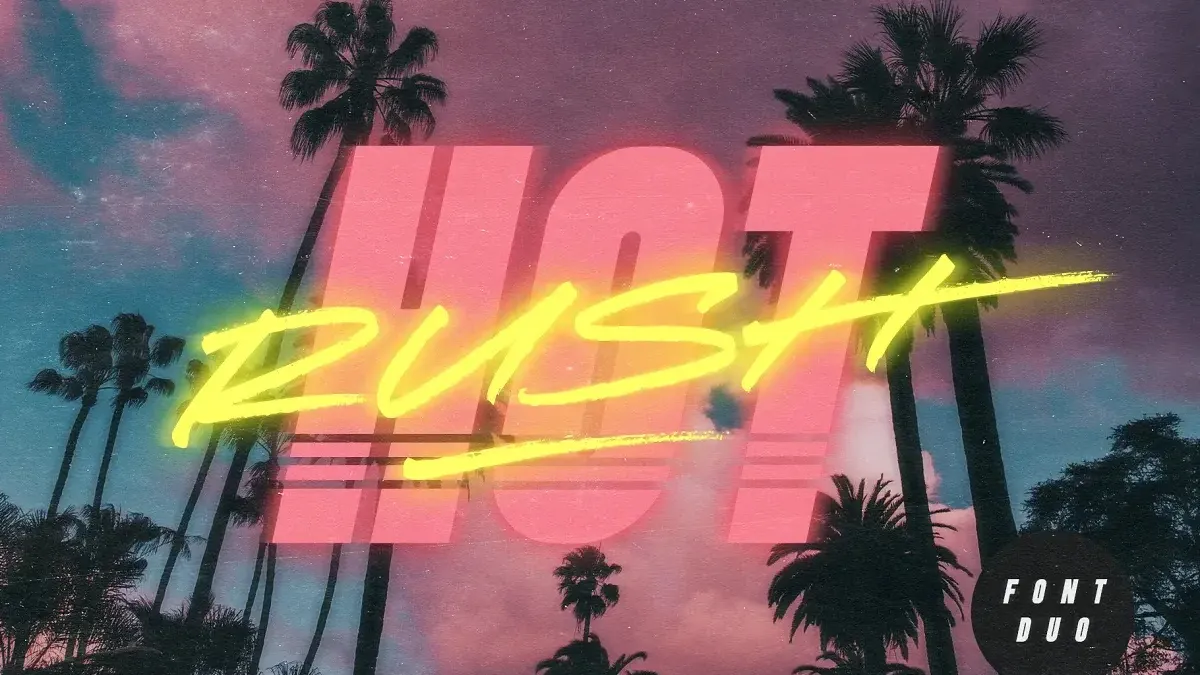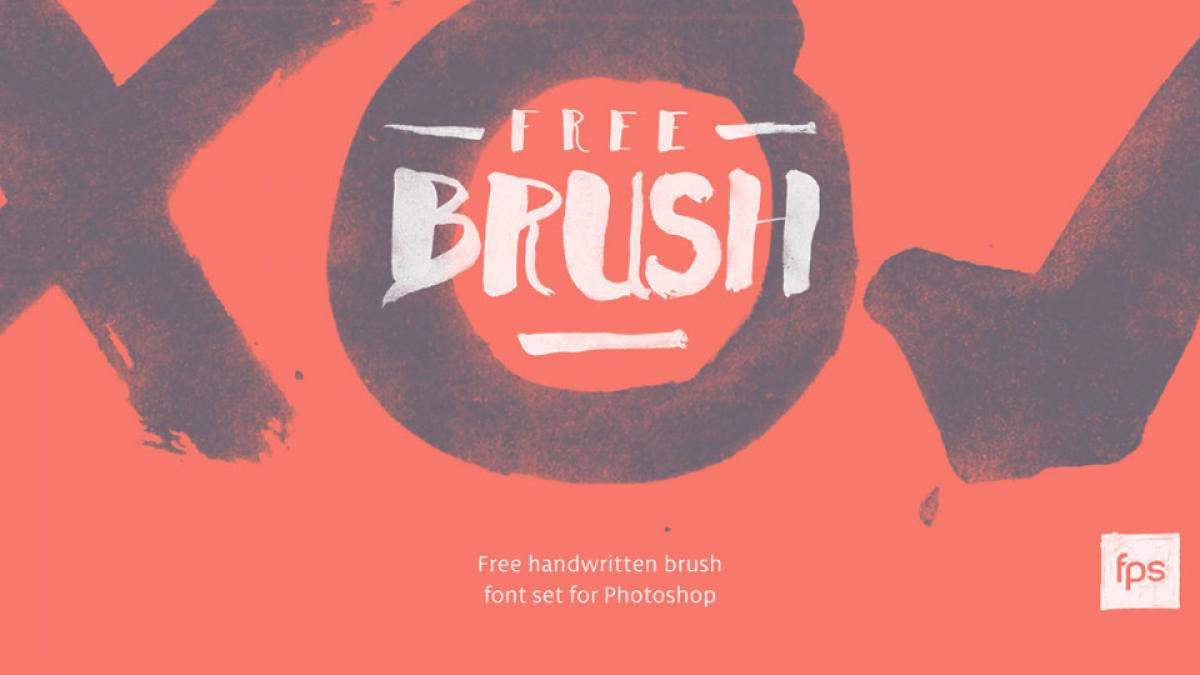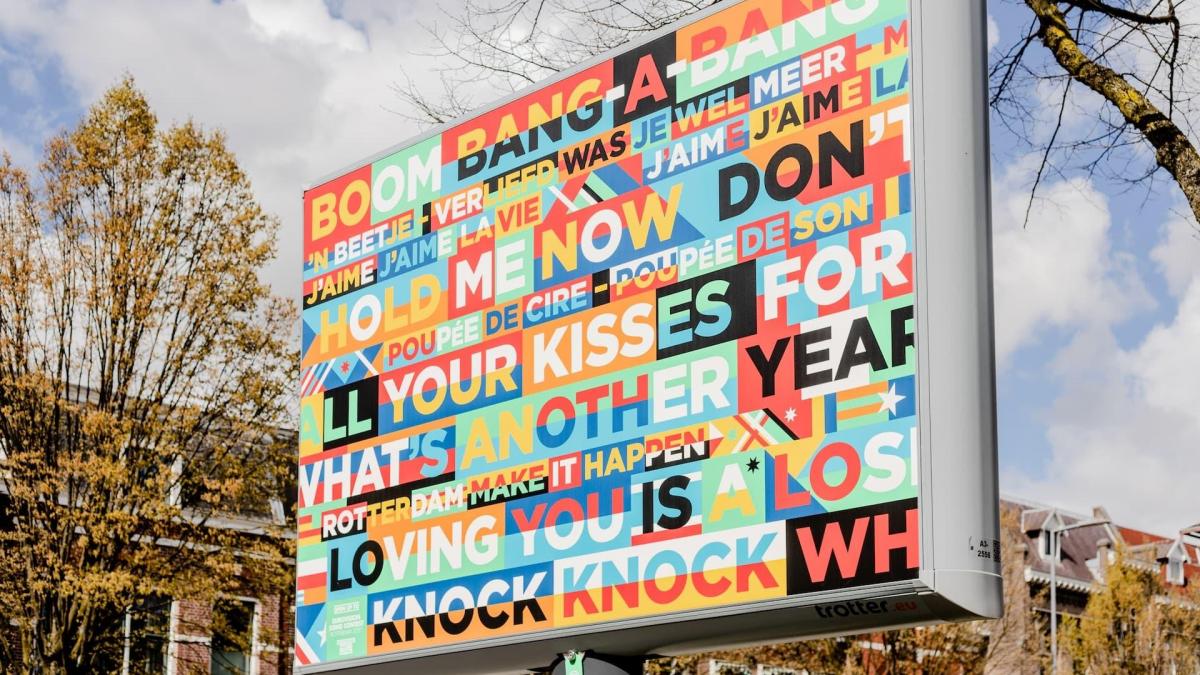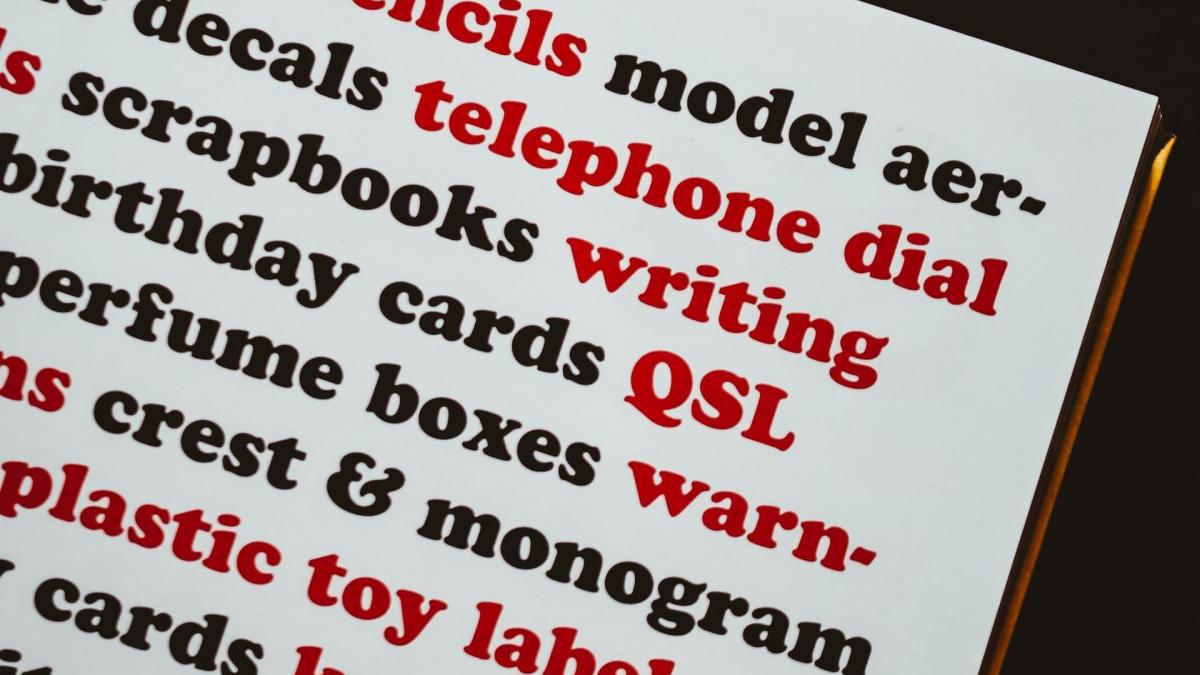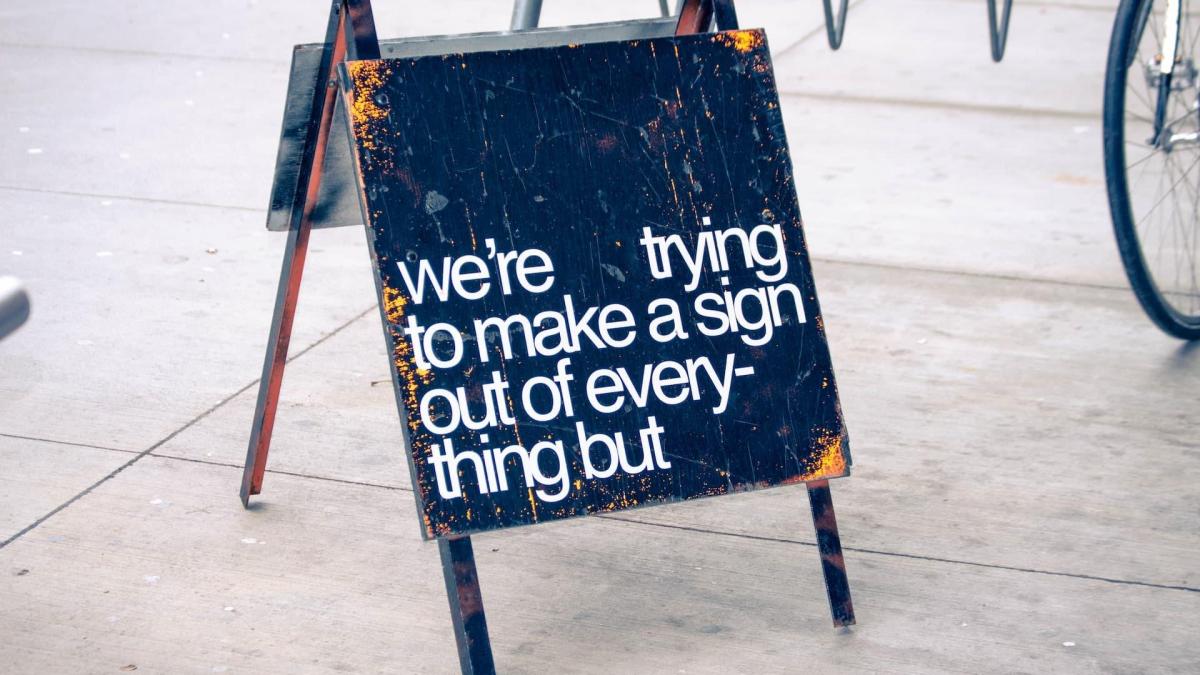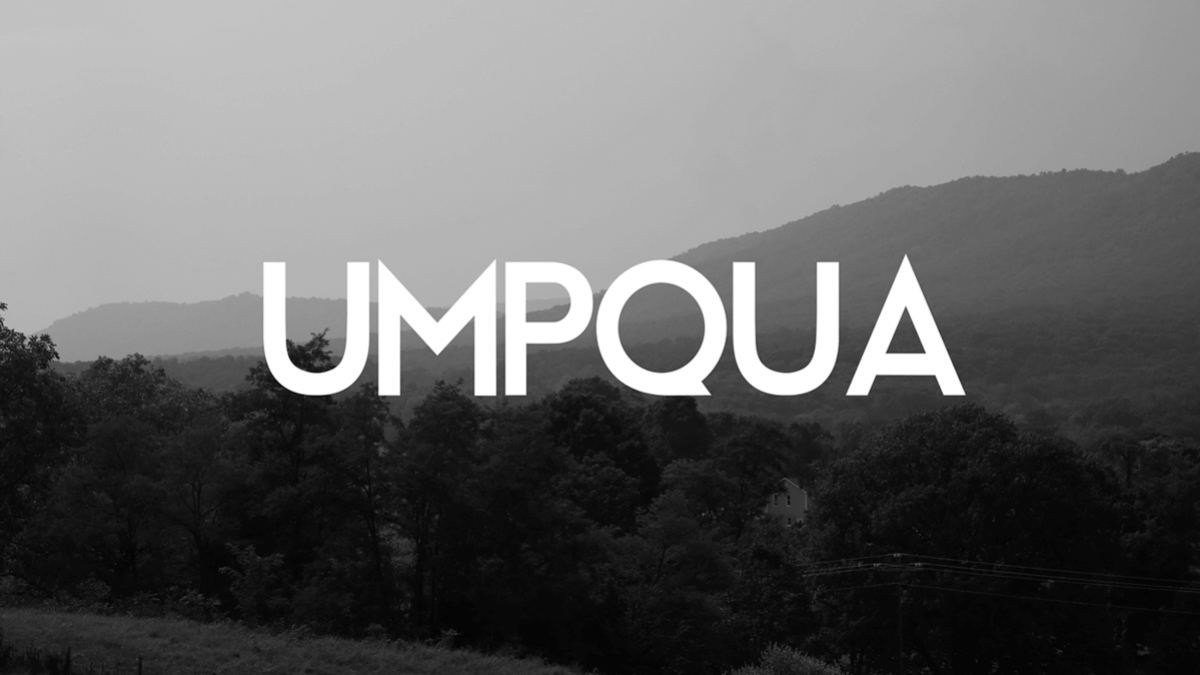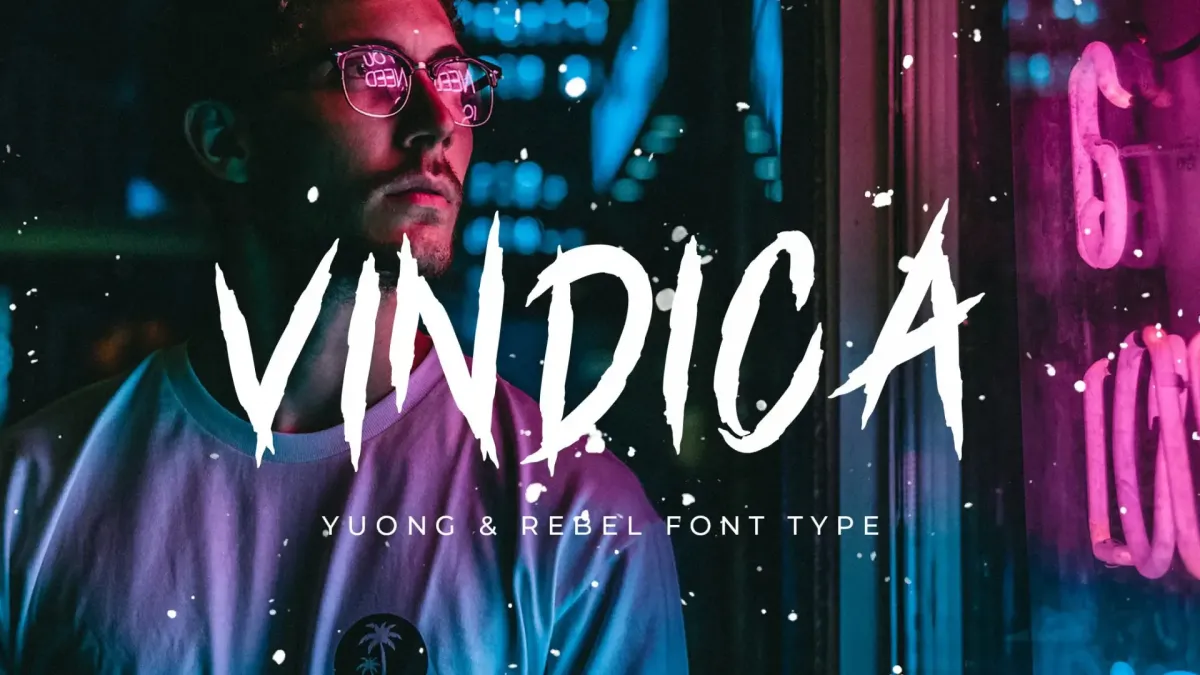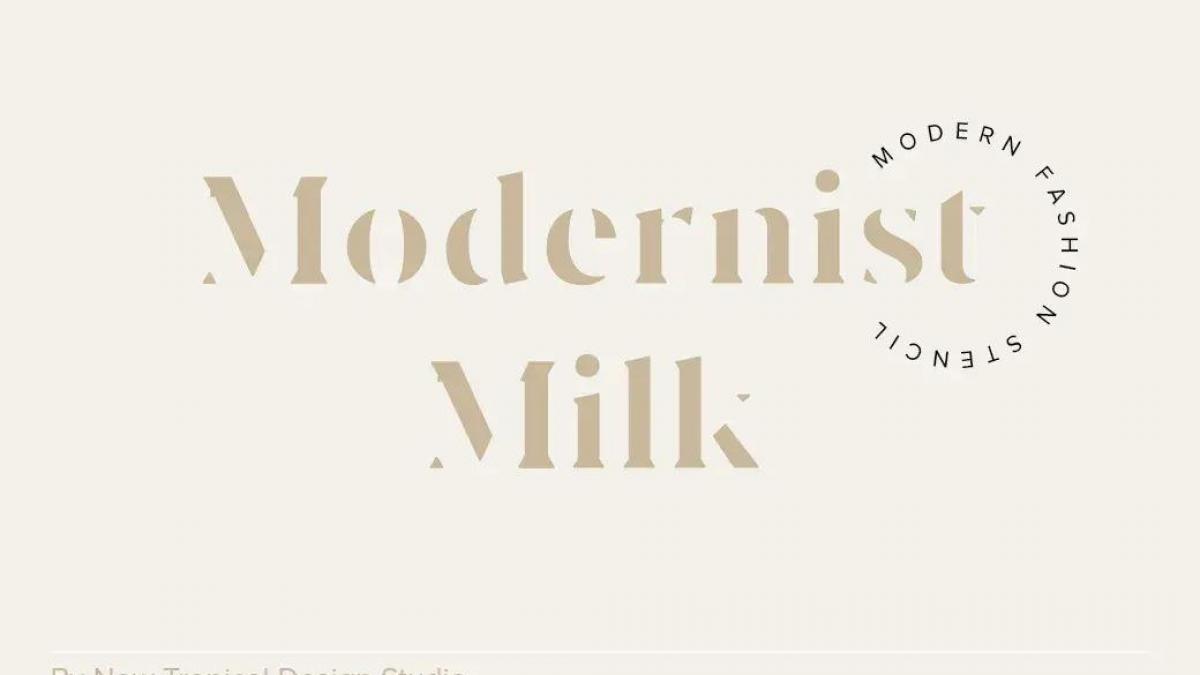
Trouvez les meilleures typographies en ligne
Que vous soyez un créateur passionné, un concepteur graphique ou un professionnel du web, notre sélection des meilleures typographies en ligne vous offre un accès instantané à des fonts uniques qui donneront vie à vos projets avec une touche de caractère et d'originalité.
Explorez une diversité de styles, des typographies épurées et modernes aux caractères audacieux et expressifs. Notre collection vous permet de trouver la typographie parfaite pour chaque projet, qu'il s'agisse de sites web percutants, de présentations professionnelles, ou de supports marketing innovants.
Donnez vie à vos idées et transformez chaque mot en une œuvre d'art typographique. Téléchargez ces typographies pour apporter une touche distinctive à vos créations tout en respectant les dernières tendances typographiques.
8. Pensez à l'accessibilité : Assurez-vous que la typographie choisie est accessible à un large public. Des polices faciles à lire, en particulier pour les personnes ayant des troubles de la vision, sont essentielles.
En fin de compte, le choix de la typographie est une décision subjective, mais en tenant compte de ces conseils, vous pouvez prendre des décisions éclairées pour sélectionner la typographie qui répond le mieux à vos besoins créatifs et communicatifs.